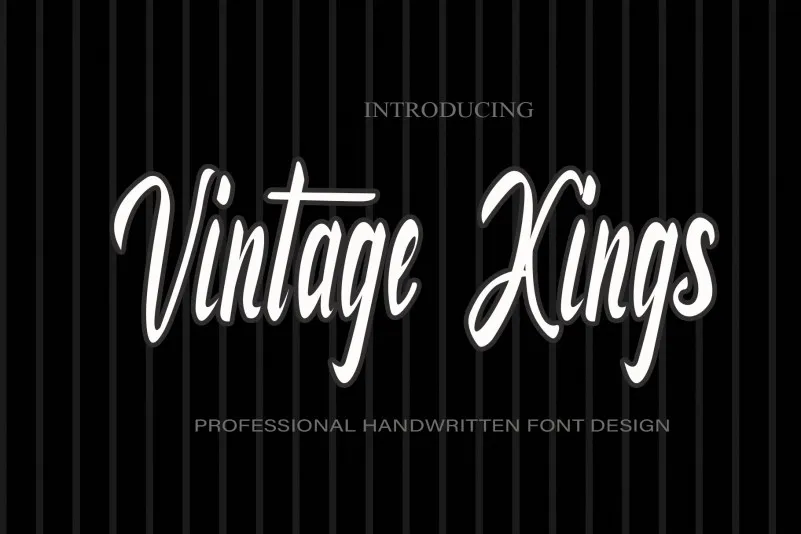
Vintage Kings Font – Download Grátis
A fonte Vintage Kings é perfeita para quem busca uma mão escrita casual e criativa. Especialmente adequada para designers de letras livres e artistas digitais, esta fonte oferece um toque pessoal a qualquer projeto que você está desenvolvendo. É ideal para gráficos de marketing digital, design editorial ou ilustrações. Sua característica mais interessante é sua capacidade de tornar seus ideias criativas viverem em uma forma visual única e vibrante. Seja ela usada para adicionar um toque especial a seu próximo projeto, a Vintage Kings vai deixá-lo surpreso com sua facilidade e versatilidade. O designer Kateengciu criou esta fonte como uma maneira de capturar o espírito livre dos anos 50 e 60. Com linhas suaves e texturas distintas, ela promete criar um impacto atraente no seu trabalho. Seja para títulos de página ou capa, headlines ou texto interno – esta fonte pode ser usada em qualquer lugar onde você desejar adicionar uma pitada de personalidade. A Vintage Kings é uma ótima opção para quem procura criar um efeito visual diferenciado que destaca seu trabalho. Com certeza, a Vintage Kings será um complemento fantástico para designers de letras livres que buscam uma fonte criativa, versátil e cheia de vida. Seja em sua própria criação ou em projetos de design para clientes, pode transformar suas ideias em arte com esta elegante fonte.